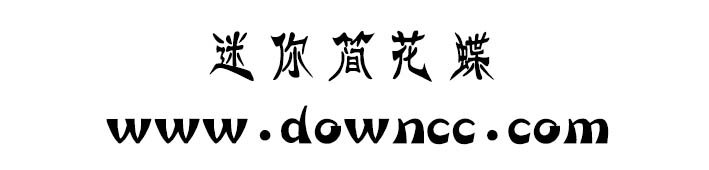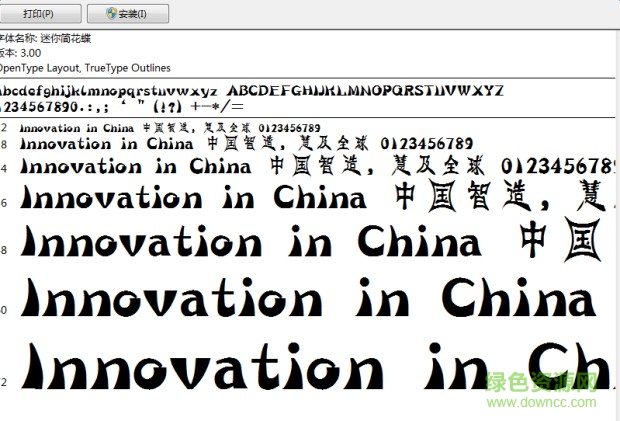
迷你簡(jiǎn)花蝶字體一款迷你字庫(kù)中的字體,它具有非常獨(dú)特的文字造型,該字體以花蝶為原形設(shè)計(jì),字體藝術(shù)效果十足,適用于名片設(shè)計(jì)、廣告設(shè)計(jì)、平面設(shè)計(jì)、雜志報(bào)刊等,有喜歡的朋友可以來(lái)綠色資源網(wǎng)下載使用!
迷你簡(jiǎn)花蝶字體就如名字一樣字體跟蝴蝶版一樣翩翩起舞,給人一種美好的心情,是那種越看越喜歡的字體。